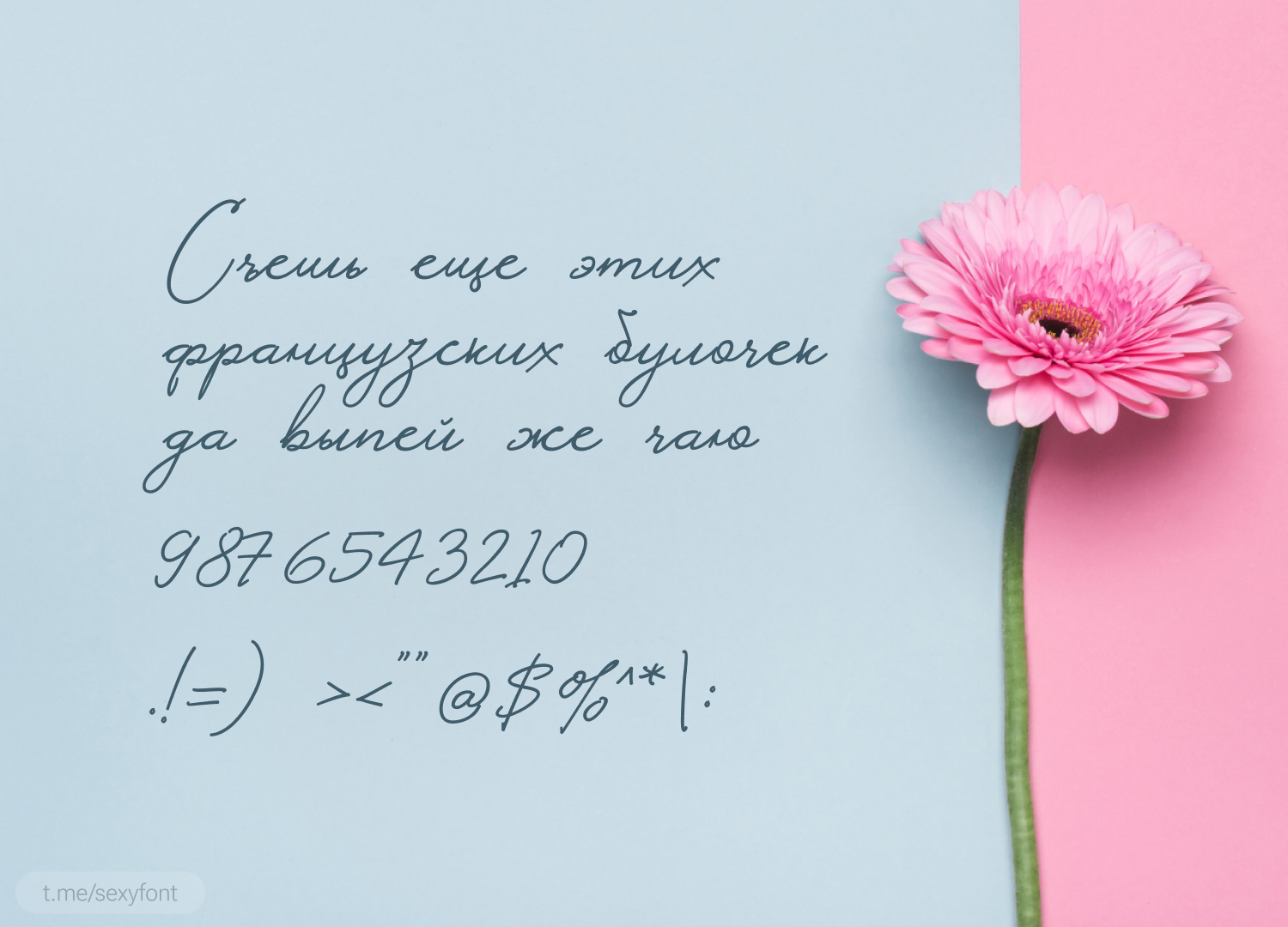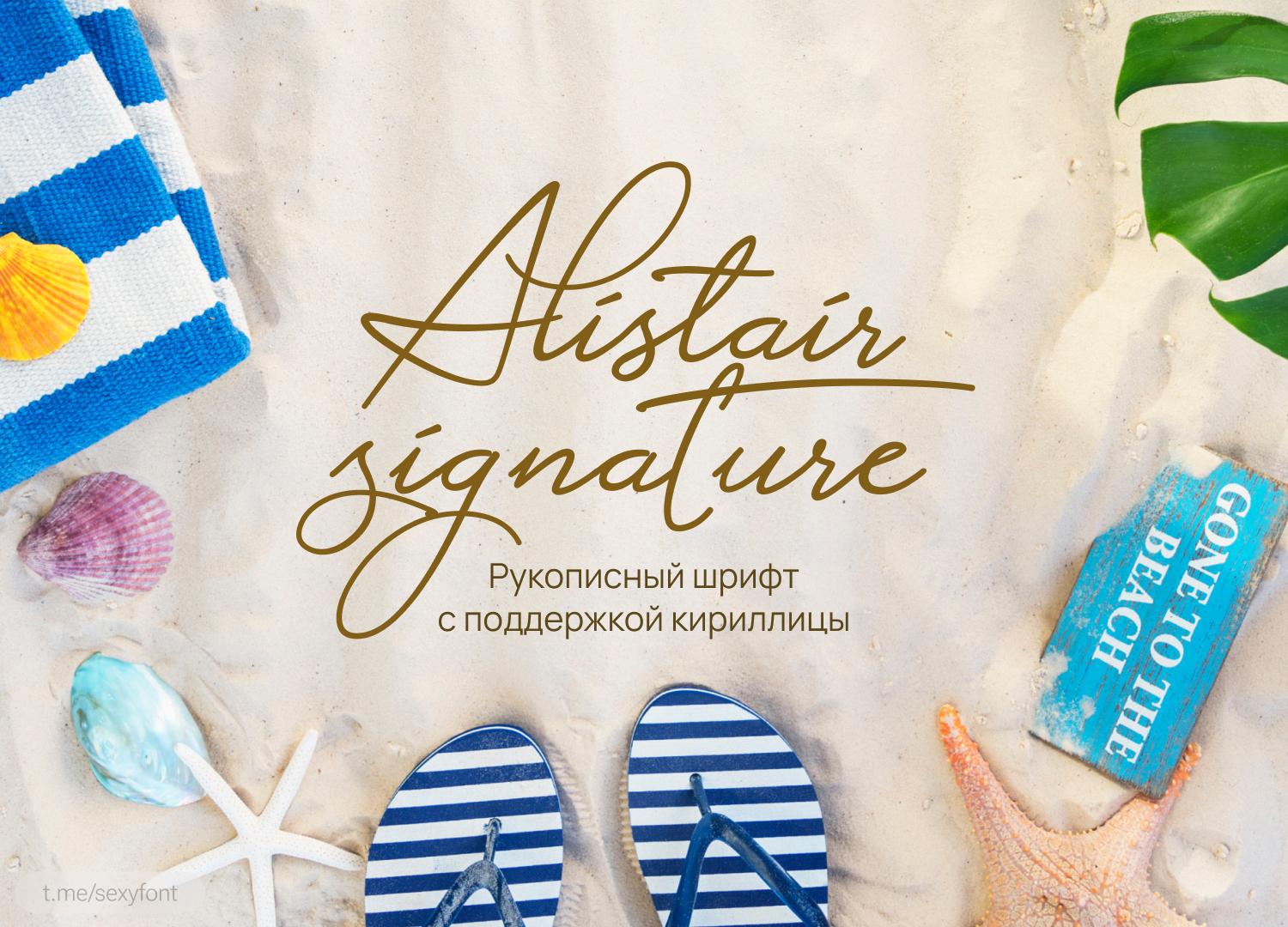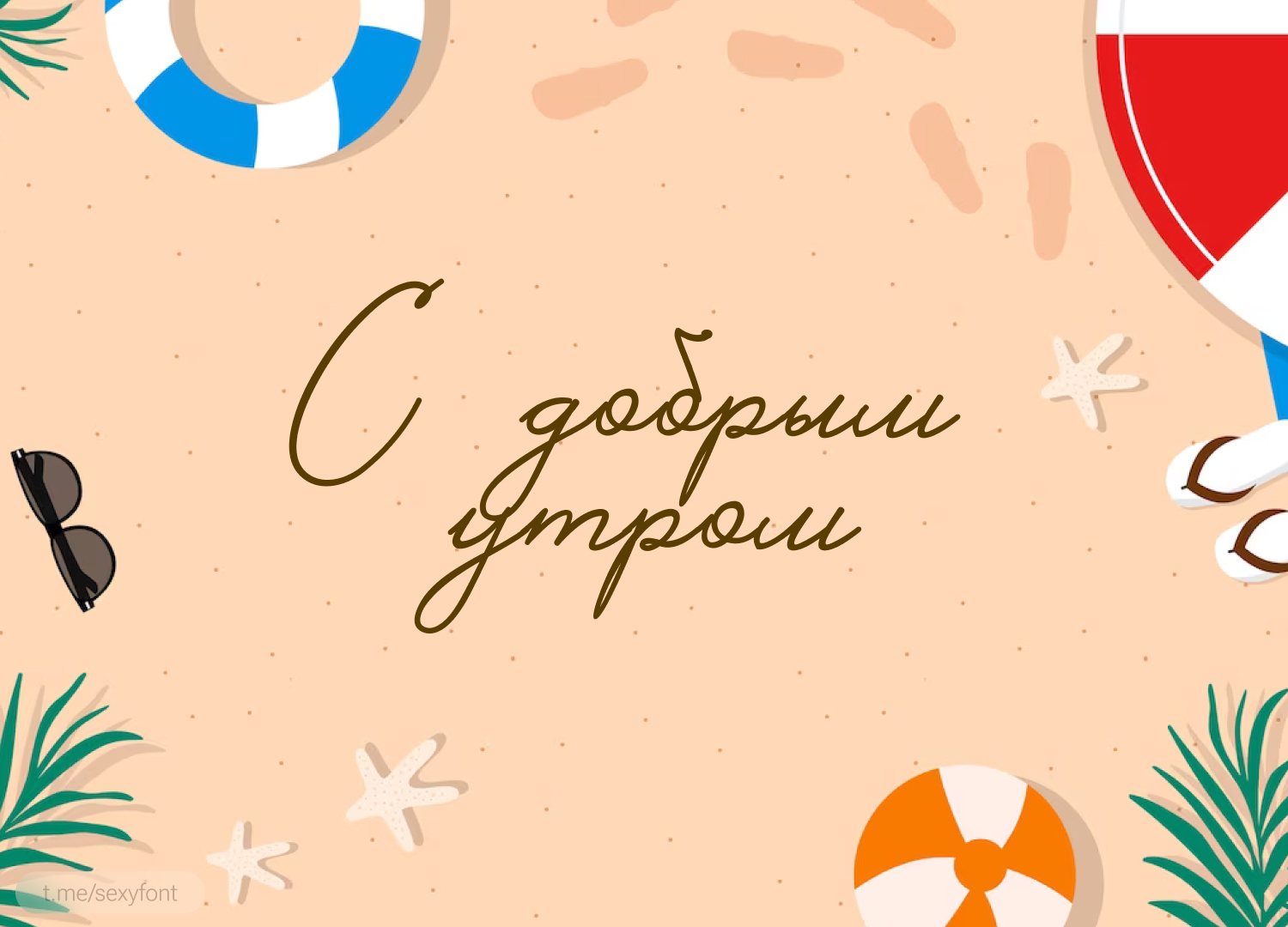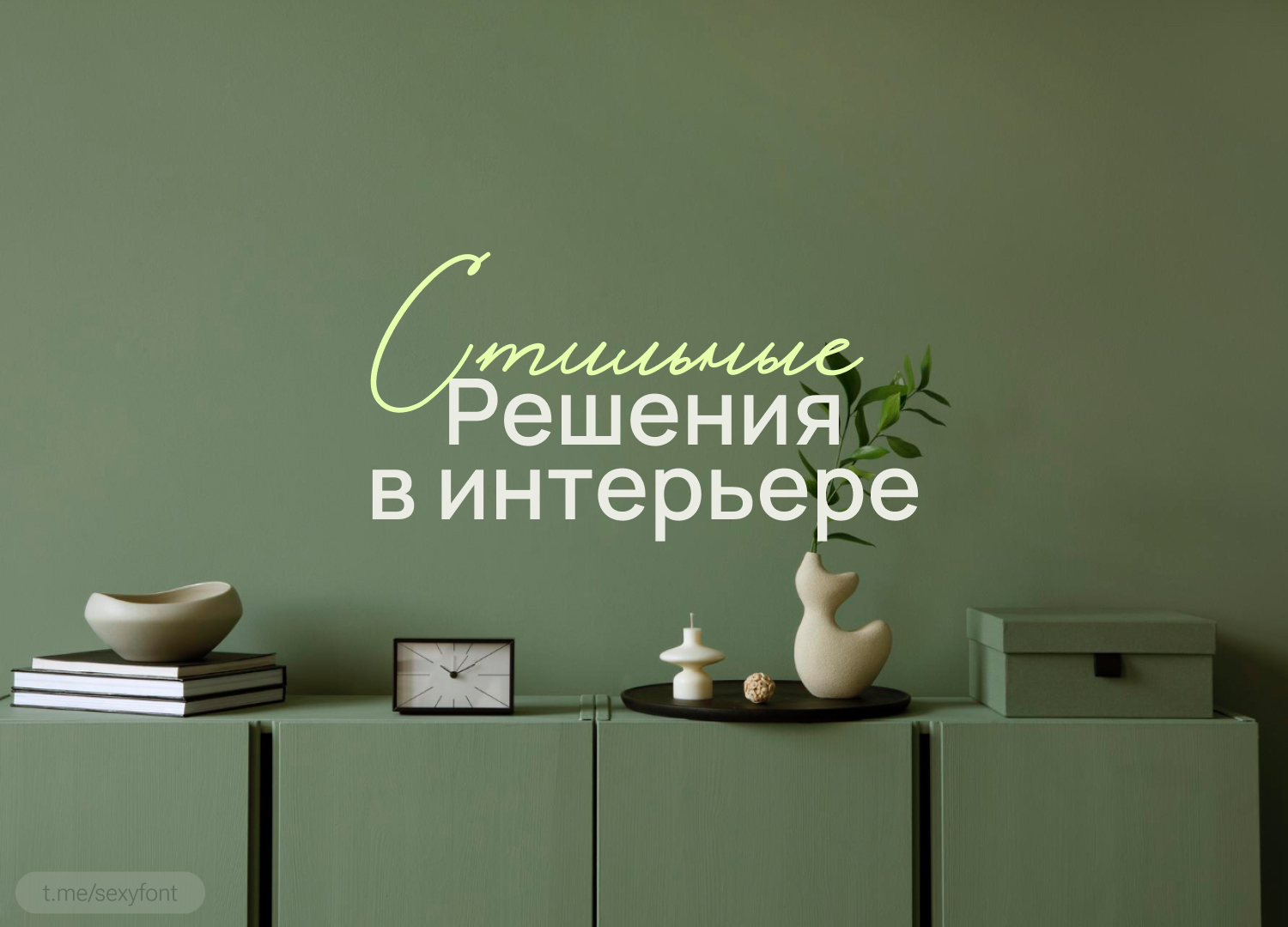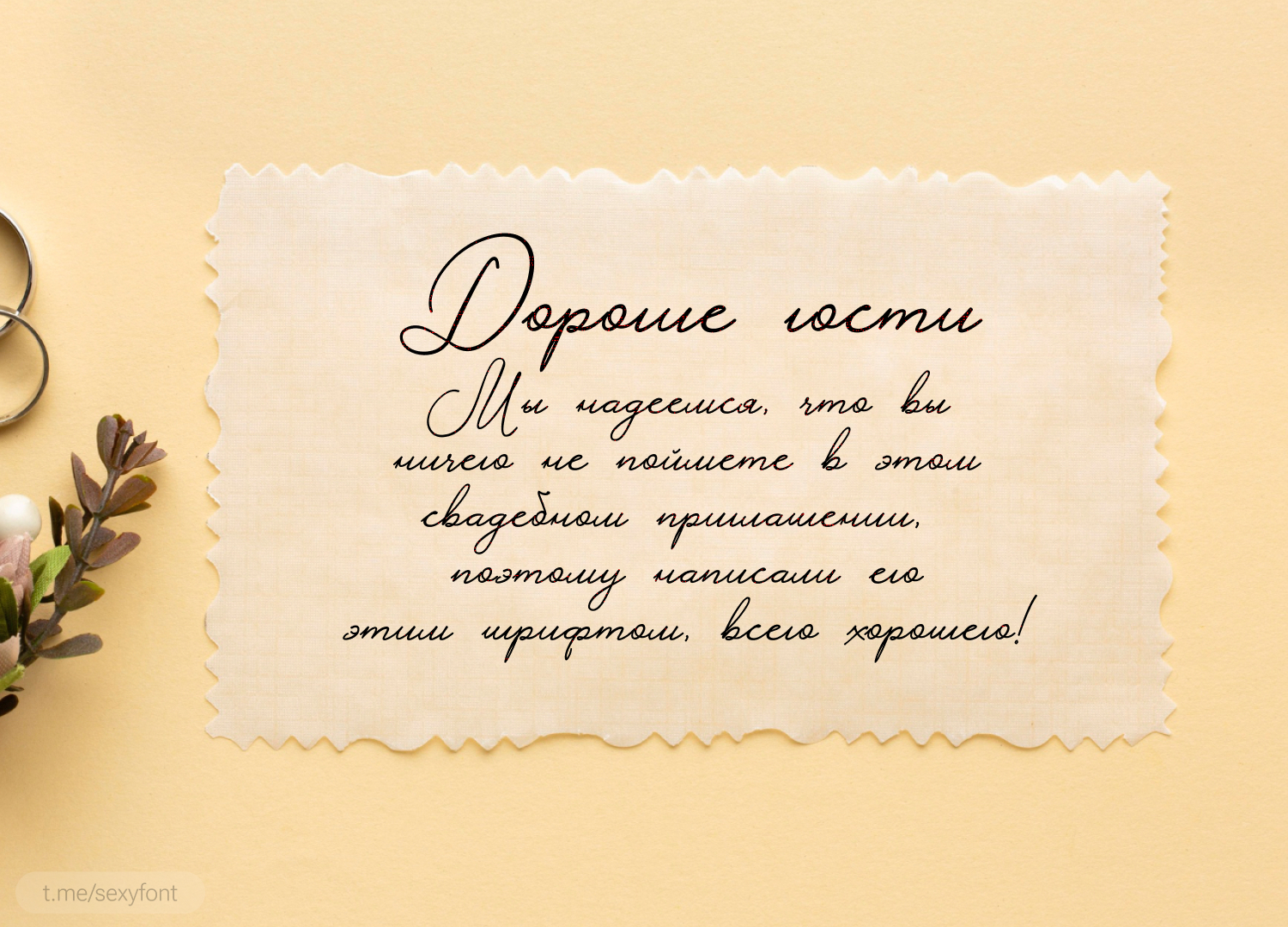
Рукописный шрифт. Кириллизация
😎 Кириллизация рукописного шрифта Alistair Signature.
Подойдет под короткие надписи, открытки. Но как и все подобные шрифты плохо считывается в длинных абзацах) Лучше использовать в парах с другими, как на 3-м слайде)